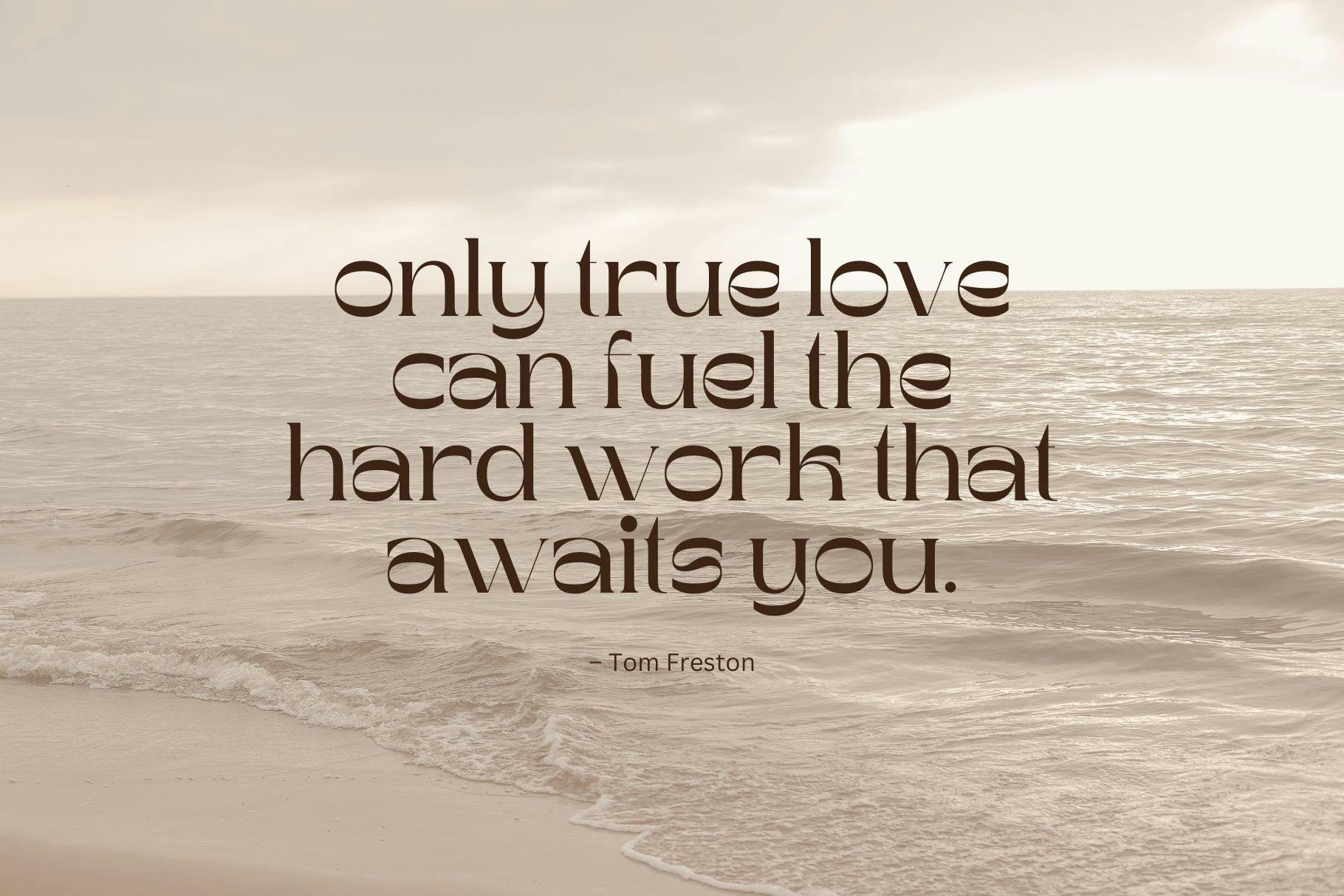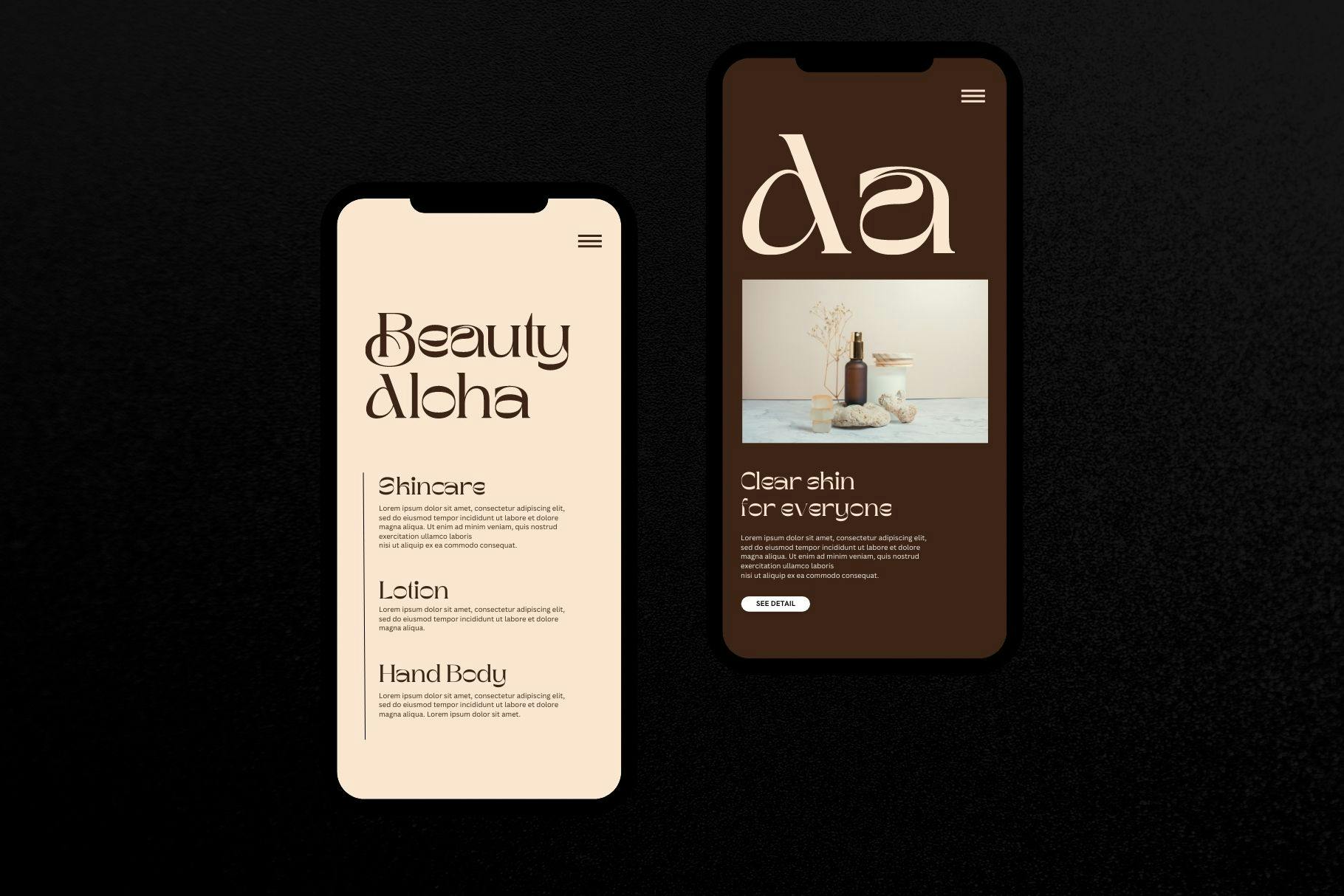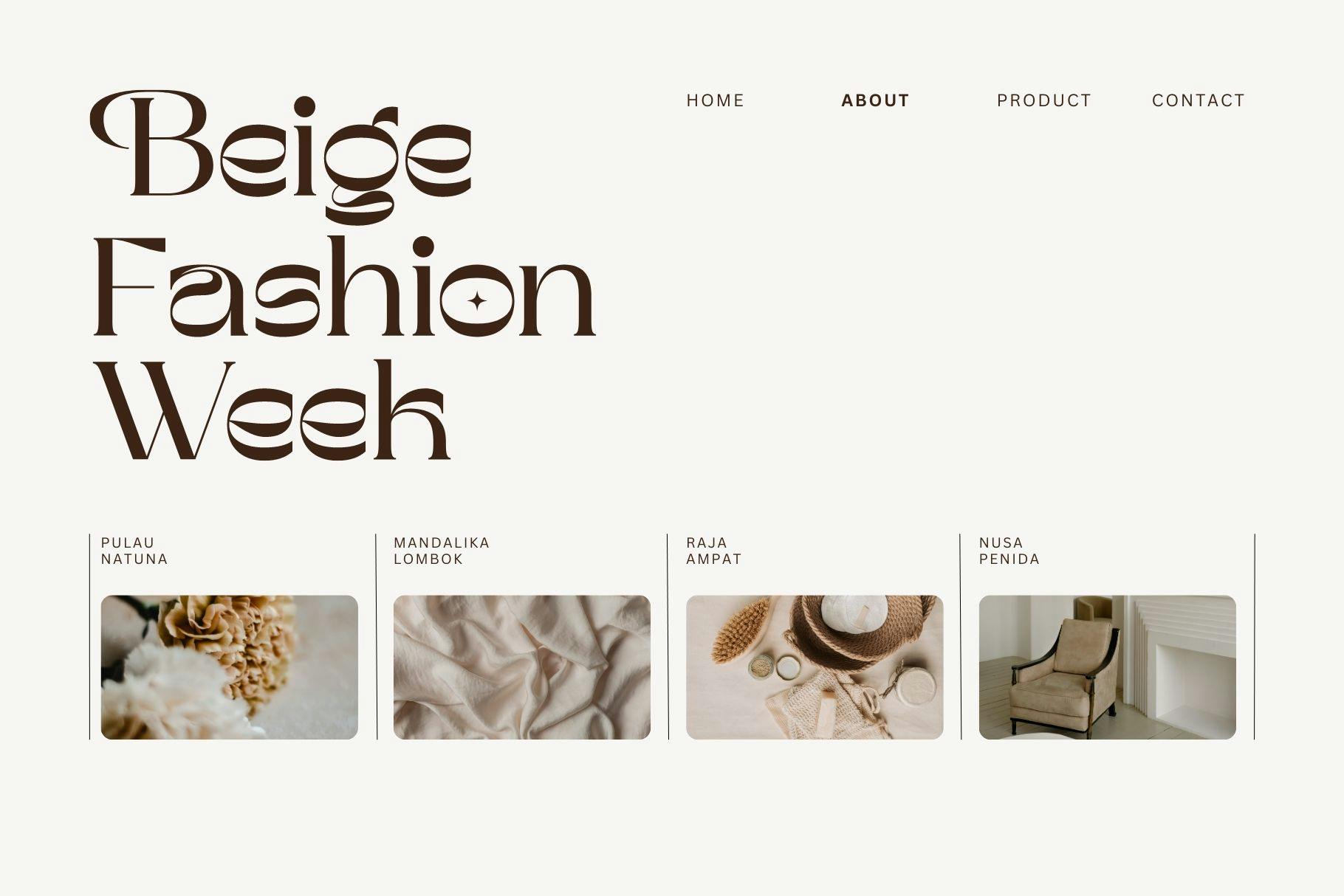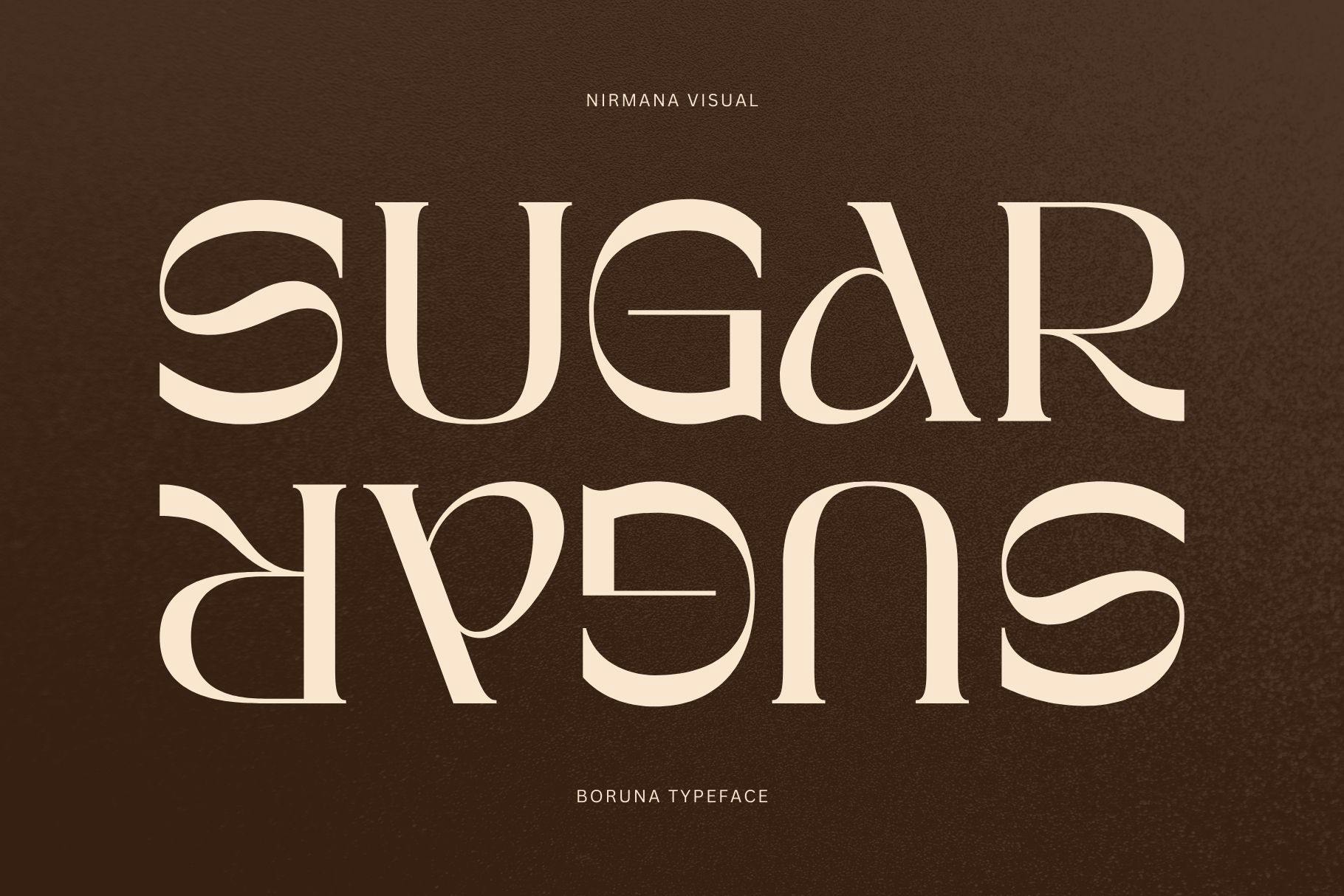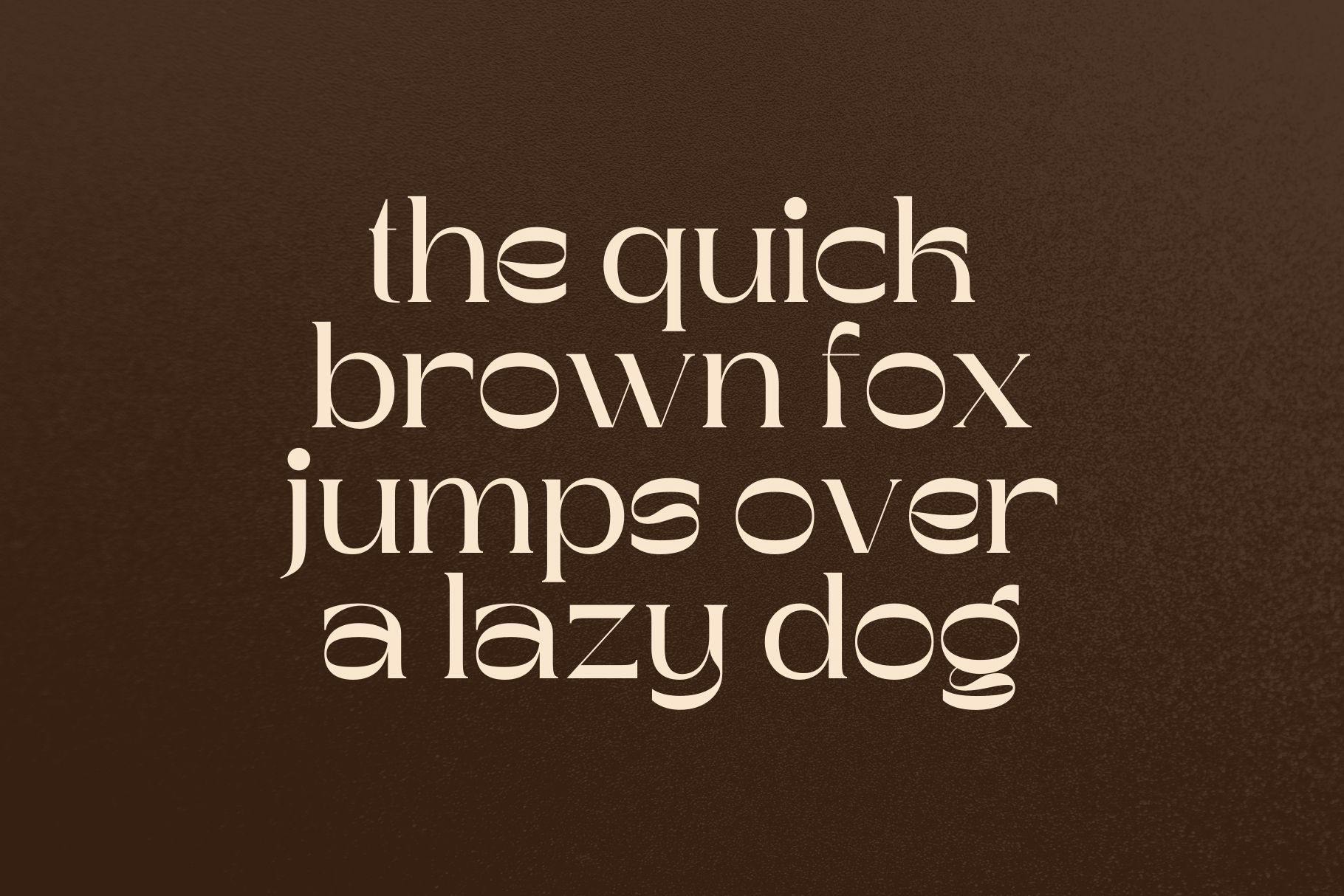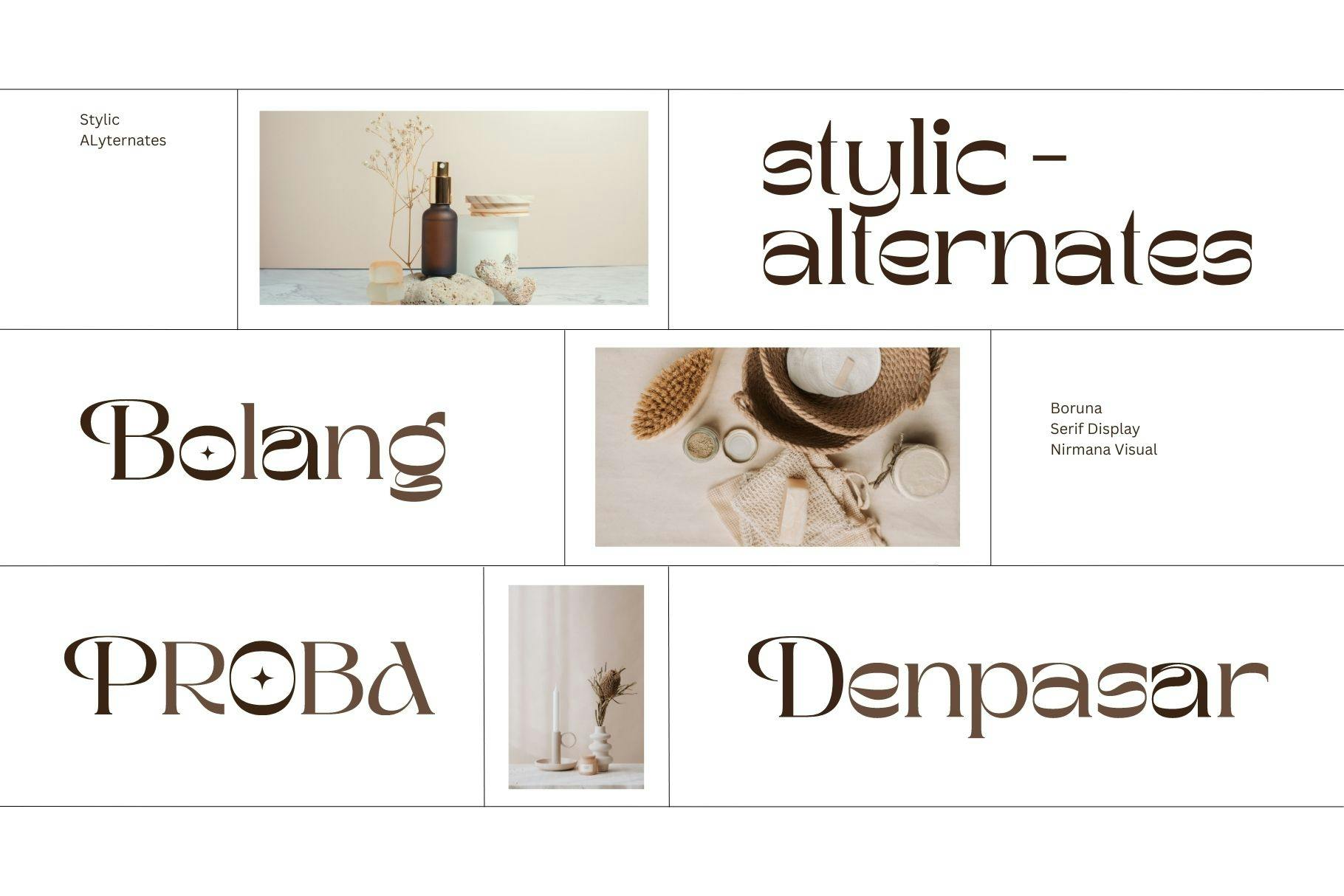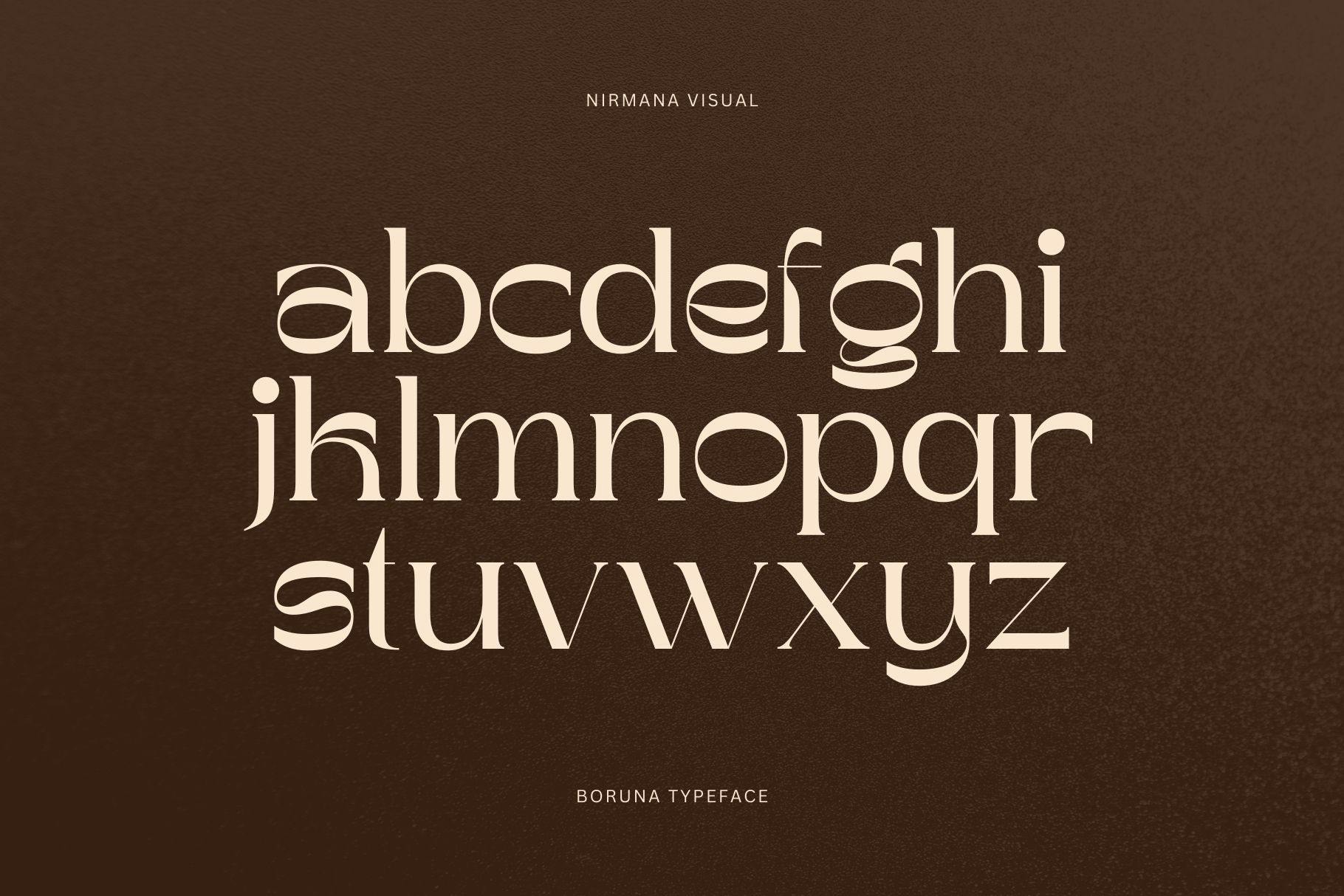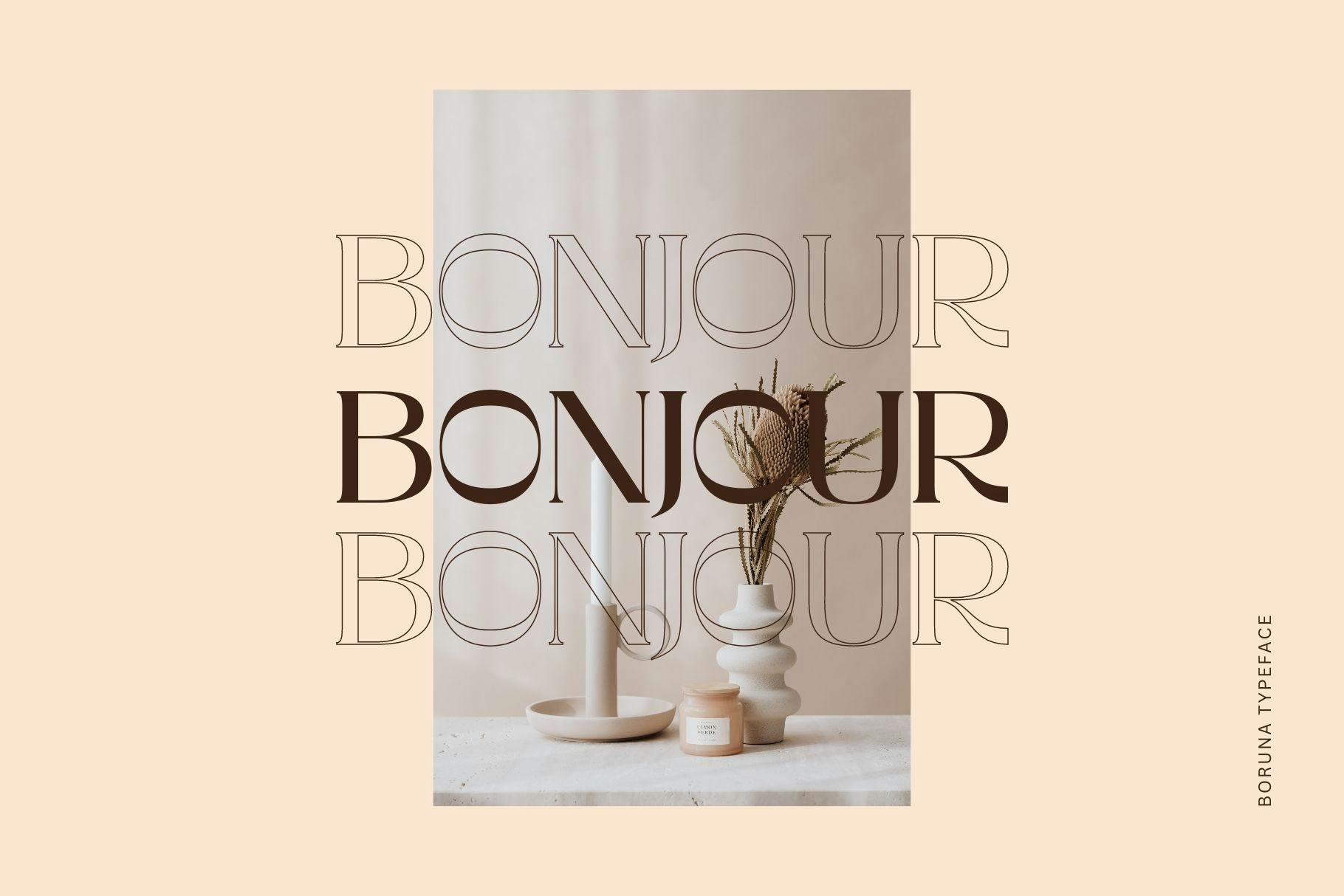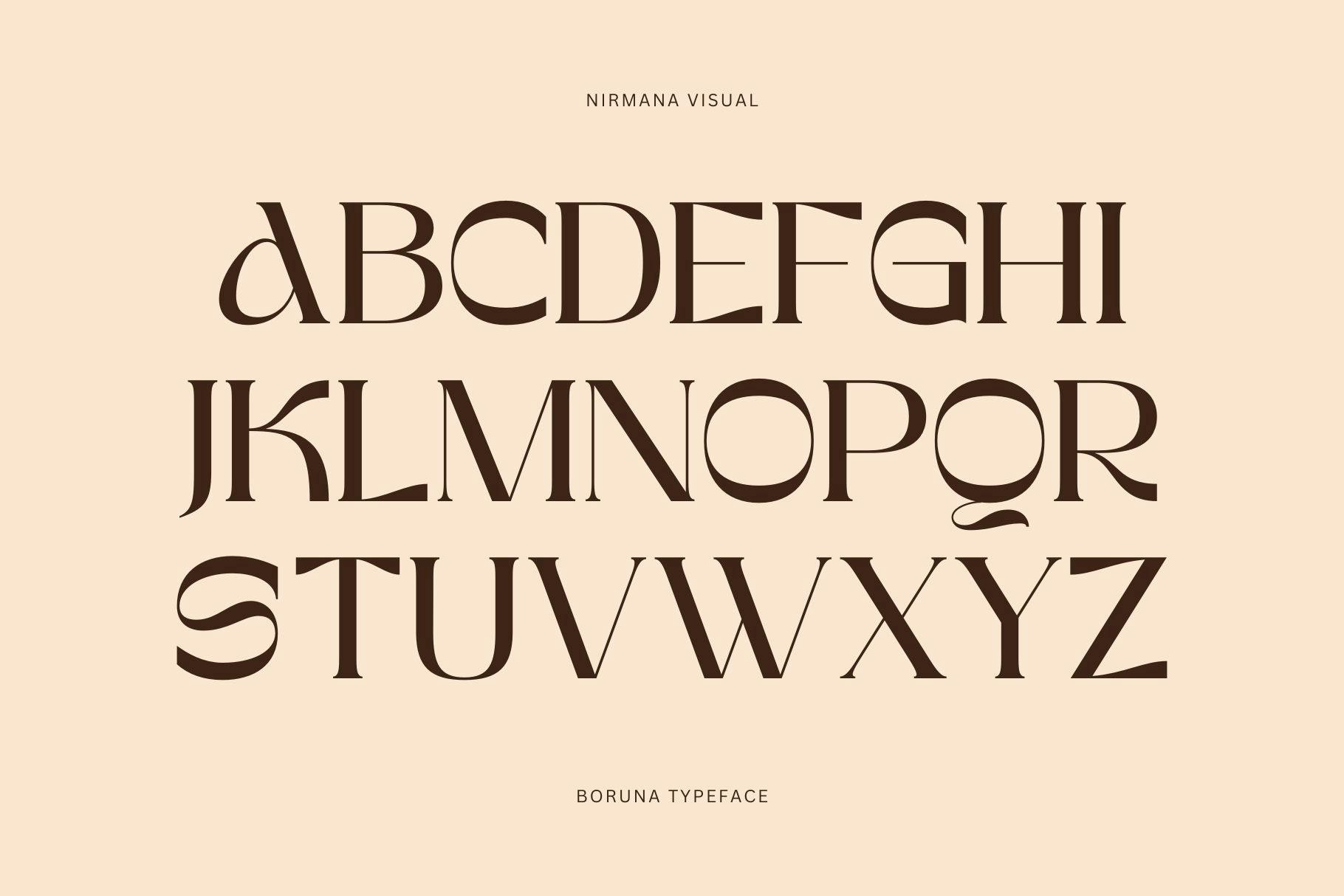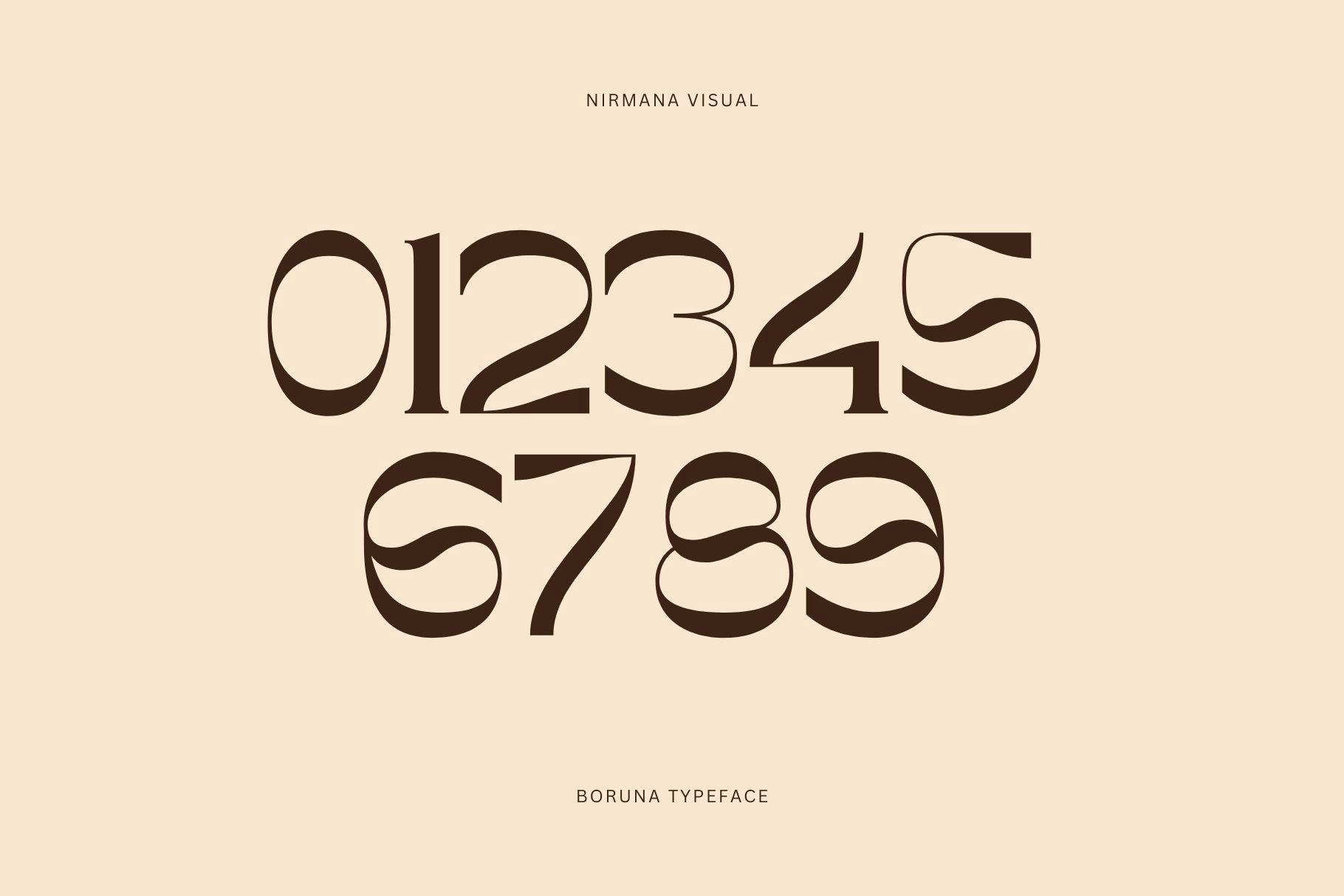
Boruna یک نوع قلم Serif Display است که زیبایی را به طراحی شما میآورد.
این فونت هارمونی زیبایی از تایپوگرافی را برای پروژههای طراحی متنوع شامل لوگو و برندینگ، پستهای رسانههای اجتماعی، تبلیغات و طراحی محصولات ارائه میدهد.